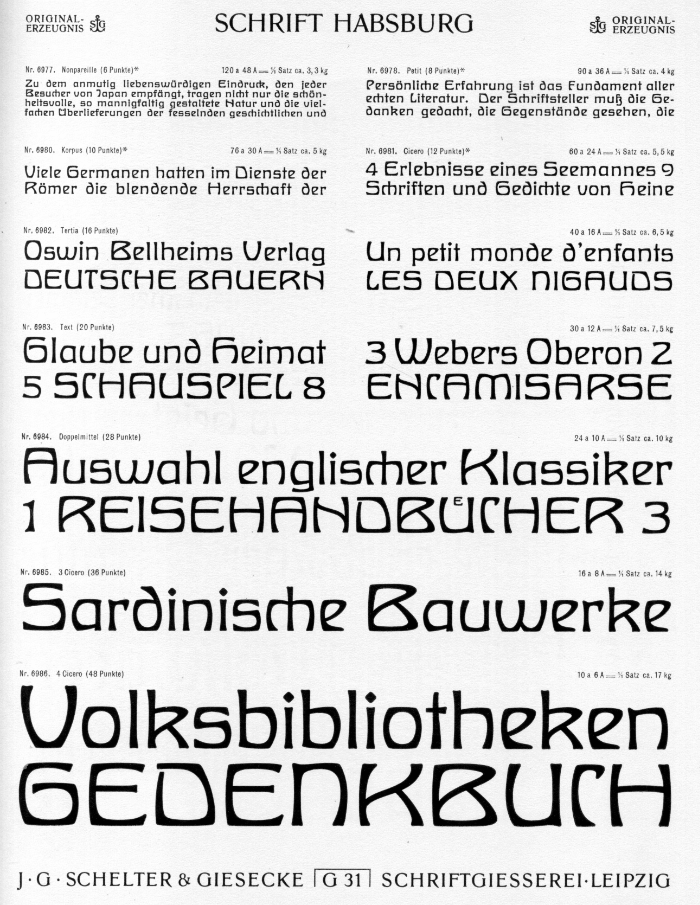
Jugendstil, die zehnte & elfte: Wittelsbach und Habsburg
Als nächstes habe ich die Habsburg ausgewählt, und zwar nur darum, weil sie ein sehr passendes Pendant zur Wittelsbach bildet, wie man schon im von mir zuallererst eingestellten Beispiel sieht.
Wer mir jetzt unterstellt, daß die Habsburg nurmehr eine breite Wittelsbach ist und ich so auf die Schnelle das Dutzend vollkriegen will, weil mir so langsam der Dampf ausgeht, könnte nicht weiter von der Wahrheit entfernt sein!
Trotzdem wäre es unangebracht, einen weiteren Thread aufzumachen. Ich habe den Titel geändert, und mache hier weiter.
Fontlab hat in der letzten Beta-version eine neue Funktion integriert, mit der man Glyphen nach belieben skalieren kann ohne die Strichstärke zu ändern. Leider klappt das noch nicht so gut, die Resultate sind noch sehr unbefriedigend. Zudem unterscheiden sich die Glyphen der Habsburg alle ein wenig von denen der Wittelsbach. Ich verbreitere also händisch.
Vom Namen her hätte ich ja eher was anderes erwartet, aber sie wirkt sehr gemütlich im Gegensatz zur schmalen Schwester. Vor Allem in den Versalien. Nur das gefräßige, eckige Pac-Man-e finde ich seltsam :-?
Nur das gefräßige, eckige Pac-Man-e finde ich seltsam
Na, dann warte mal bis Du die Umlaute siehst!
Mit der Gemütlichkeit hast Du recht, besonders scheint mir  die Schrift für die Naturkostetikettierung geeignet zu sein. Oder auch für den Schriftzug einer Waldorfschule.
Mit den Namen mancher dieser Schriften tue ich mich auch schwer. Sie sind für meine Kundschaft schwer auszusprechen, und wenig einprägsam. Da es hier aber um Wiedererweckung, und nicht um Verwertung geht, fühle ich mich gebunden, die alten Namen beizubehalten.
Fertig. Herrgott, das war eine Tortur. Es ist schon spät, hier nur mal ein Schmankerl mit beiden Schriften, nur zum angucken. Morgen mehr.
Hier nun eine richtige Probe. Ich hatte Anfang des Monats angenommen, die fertige Wittelsbach einfach in die Breite ziehen zu können, um so, vielleicht mit einigen wenigen Justierungen, die Habsburg  zu gewinnen. Das war eine fatale Fehleinschätzung. Die Formen stimmen nur in den Ansätzen überein, unterscheiden sich bei näherer Betrachtung aber drastisch von denen der Wittelsbach.  Auch Spacing und Kerning konnte ich nicht extrahieren. Nichts stimmte, alles war verkehrt, und wurde auch nicht besser. Am Ende fing ich nochmal neu an, so wie ich es mit jeder anderen Schrift auch mache. Das führte schließlich zum Erfolg. Gestern Abend konnte ich dann den "fun part" machen: drei verschiedene Formen der Umlaute, die alle so in meinem Quellenmaterial gezeigt werden. Beim Erstellen der Probe fielen mir dann noch eine paar Fehler auf, die sind aber schnell behoben. Jetzt auf zum Endspurt!
Und zum guten Schluß stelle ich noch einmal die erste, hier gezeigte, Anwendung beider Schriften ein – diesmal aus meinen eigenem Gewächs gekeltert!